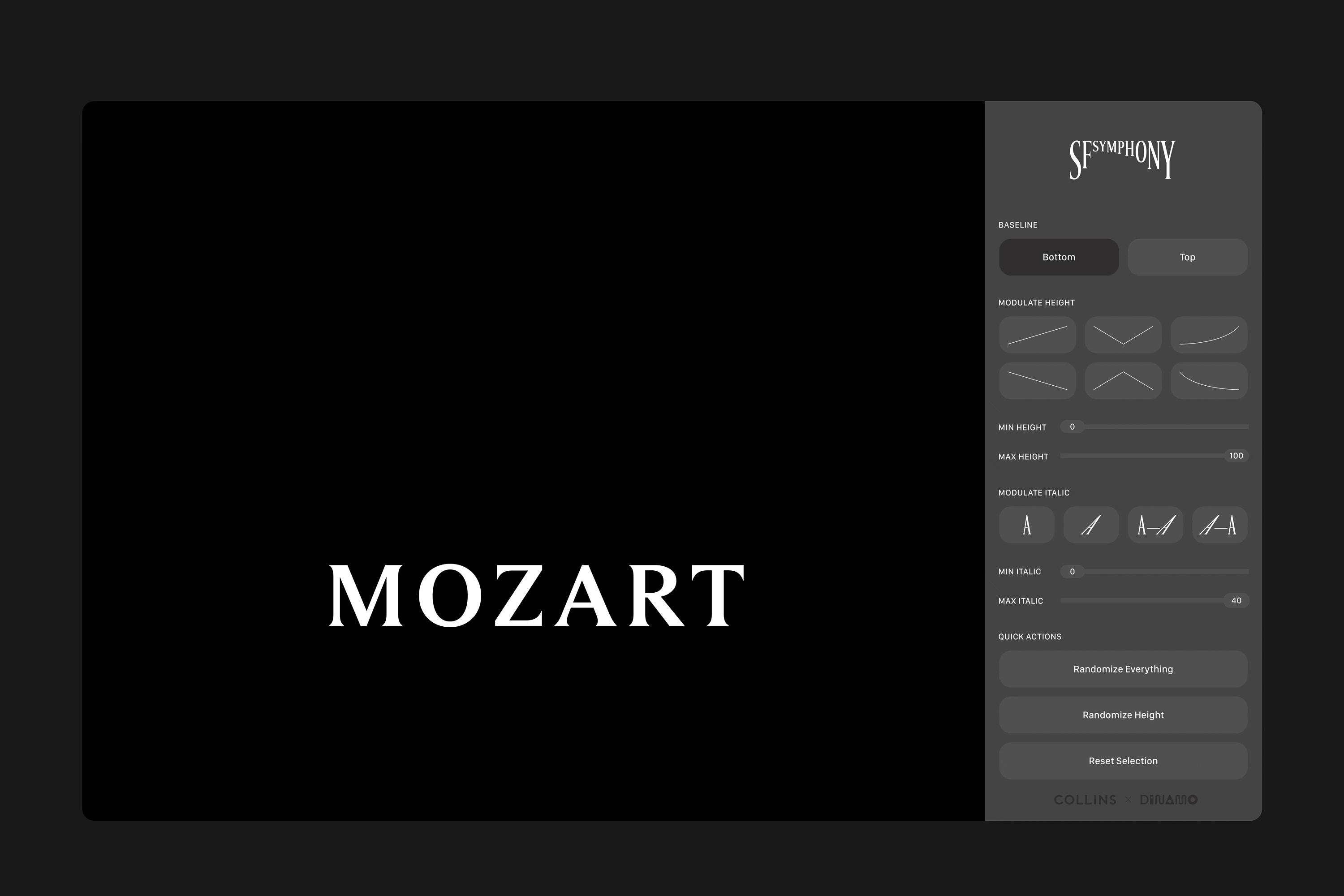
Künstler und Marken durch Klang und Musik verbinden.
Typografie kann jetzt noch mehr
Quer über alle Branchen hinweg erfreuen wir uns an einem langsamen, aber stetigen Wandel hin zu einer ganz neuen Interaktivität von Markenschriften. Die Technologie der variablen Fonts schafft neue Möglichkeiten responsiver und interaktiver Schriftwahrnehmung für Marken und ihre Zielgruppe. Nie zuvor war Typografie ein so integraler Bestandteil der Markenidentität.
Ein sehr aktives Feld ist das der visuellen Effekte im Kontext kinetischer Typografie. In den letzten fünf Jahren haben Künstler wie Kiel Mutschelknaus und Unternehmen wie DIA (gegründet von Creative Director und Musiker Mitch Paone sowie Managing Partner Meg Donohoe) die Grenzen beweglicher Typografie neu ausgelotet. In der Musik- und Klangindustrie gibt es eine schier unerschöpfliche Quelle an unglaublichem Talent.
Diese interaktiven Schrifterlebnisse beruhen auf der Kompatibilität von Schrift mit allen Medienformaten. Durch die Entwicklung variabler Fonts haben wir auch Achsen erschaffen, die Fonts immer stärker zu typografischen APIs werden lassen, in denen das Look and Feel von Worten durch Klang und Licht gesteuert werden kann. Dieser responsive Typografie-Ansatz wird es Fonts schon bald ermöglichen, unsere persönlichen Profile zu repräsentieren – Fonts, die uns persönlich ansprechen und sich unserer Umgebung anpassen.
Man sollte meinen, dass wir auf diese Entwicklung gut vorbereitet sind und ihr vielleicht sogar entgegenfiebern. Mit dem Erstarken der sozialen Medien in den letzten 20 Jahren und dem zuletzt immer größer werdenden Anteil von Kurzvideoinhalten wurde diese Entwicklung enorm verstärkt und in eine bildgewaltige Komposition verwandelt, in der jedes Pixel nach Aufmerksamkeit schreit. Heute beinhaltet praktisch jedes YouTube Short, jedes Video auf TikTok und jedes Instagram Reel typografische Elemente – von rudimentärer, „info-tektonischer“ Rahmentypografie über grafische „Violators“ und Speech-to-text bis hin zu rein typografischen Bewegtbildern. Der Content wird über alle Kanäle verteilt und passt sich dabei den jeweiligen Strukturen an. Dabei werden die Inhalte verändert, weiterentwickelt, neu gemischt und erscheinen am Ende in gänzlich neuer Gestalt. Die Medien passen die Inhalte je nach Zielgruppe an, und diese reagieren mit geballter Aufmerksamkeit, wenn Form und Inhalt bei ihnen Anklang finden.
Jonathan Mak nutzt Schallwellenformen, um Buchstaben und Grafiken zu zeichnen. In seiner Arbeit erforscht er die Beziehung zwischen Hören und Sehen. Wir sehen, was wir hören.
Alles kombiniert: Sonotype.
Gemeinsam mit Audiosocket haben wir ein Projekt entwickelt, das diese losen Fäden zusammenführt. Dabei ging es um die Frage, wie Kreativschaffende den Zusammenhang zwischen Klang und Typografie nicht nur erforschen, sondern beide Sinne in einsatzbereiten Design-Assets miteinander verbinden könnten.
Das Ergebnis ist Sonotype, eine App, die Typografie und Klang mithilfe von KI so miteinander korreliert und kontrastiert, dass wir Klänge in Typografie sehen und Typografie in Klängen hören können.
In der Zukunft werden die Grenzen von Ausdrucksmedien neu definiert, und Sonotype ist ein erster Schritt in Richtung dieser Entwicklung – ein kreatives Tool, das Klang und Schrift miteinander kombiniert. Wir hoffen, dass das Niederreißen der bisherigen Medienbarrieren neue Möglichkeiten für Entdeckungen und unerwartete Ausdrucksmöglichkeiten eröffnet.